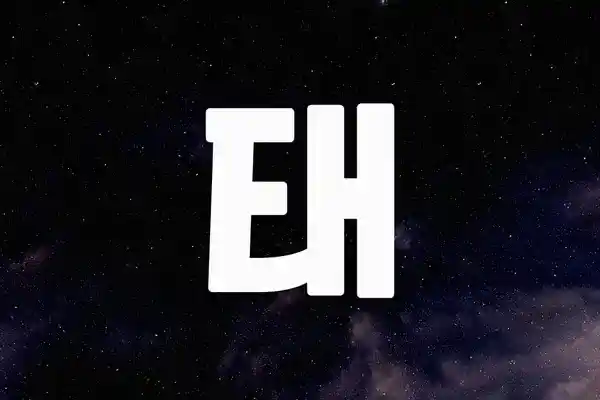
태나다체는 사진 및 동영상 편집기를 제공하는 태나다앱에서 사용하는 태나다 전용서체로, 스텐실의 특징을 적용해 독특한 인상을 주는 폰트이다.
위의 이미지에서 보듯이 태나다체는 자음의 일부 획을 의도적으로 끊은 형태로, 전체적으로는 네모틀 구조에 넓은 자폭과 곧은 획을 사용함으로써 가독성이 좋아서 제목용 서체에 어울리는 글꼴이다.
해당 태나다체는 자음 중 일부 획인 끊어진 형태인 스텐실 특징이 가장 두드러지지만, 이외에도 손글씨의 자연스러운 획순을 따라 초성과 중성이 만나는 부분이 자연스럽게 연결되어 깔끔한 느낌을 주는 폰트이다.
참고로, 해당 태나다체는 국문과 영문 그리고 KS 혼용 사용 시에도 형태적인 통일감을 유지하도록 디자인됐다. 특히 해당 태나다체는 스텐실 스타일의 폰트 특징이 도드라지므로 3D로 구현할 때 더욱 매력적이다. 실제로 태나다 전용서체이므로 그래픽 편집기인 태나다 앱에서 해당 태나다체를 활용하여 3D 효과를 구현할 수 있다.
위에서 태나다체 미리보기에서는 스텐실의 특징을 담은 자음이 없어서 해당 부분은 확인할 수 없지만, ㅎ과 ㄹ에서 태나다체가 가독성을 확보하려고 굵기 및 곡선을 조절한 형태는 확인할 수 있다. 이렇듯 해당 ttf 포맷의 글꼴 파일이 담긴 폴더에서 보기 옵션을 아주 큰 아이콘으로 설정하면 해당 글꼴이 어떠한 모양인지 가늠할 수 있어 편하다.